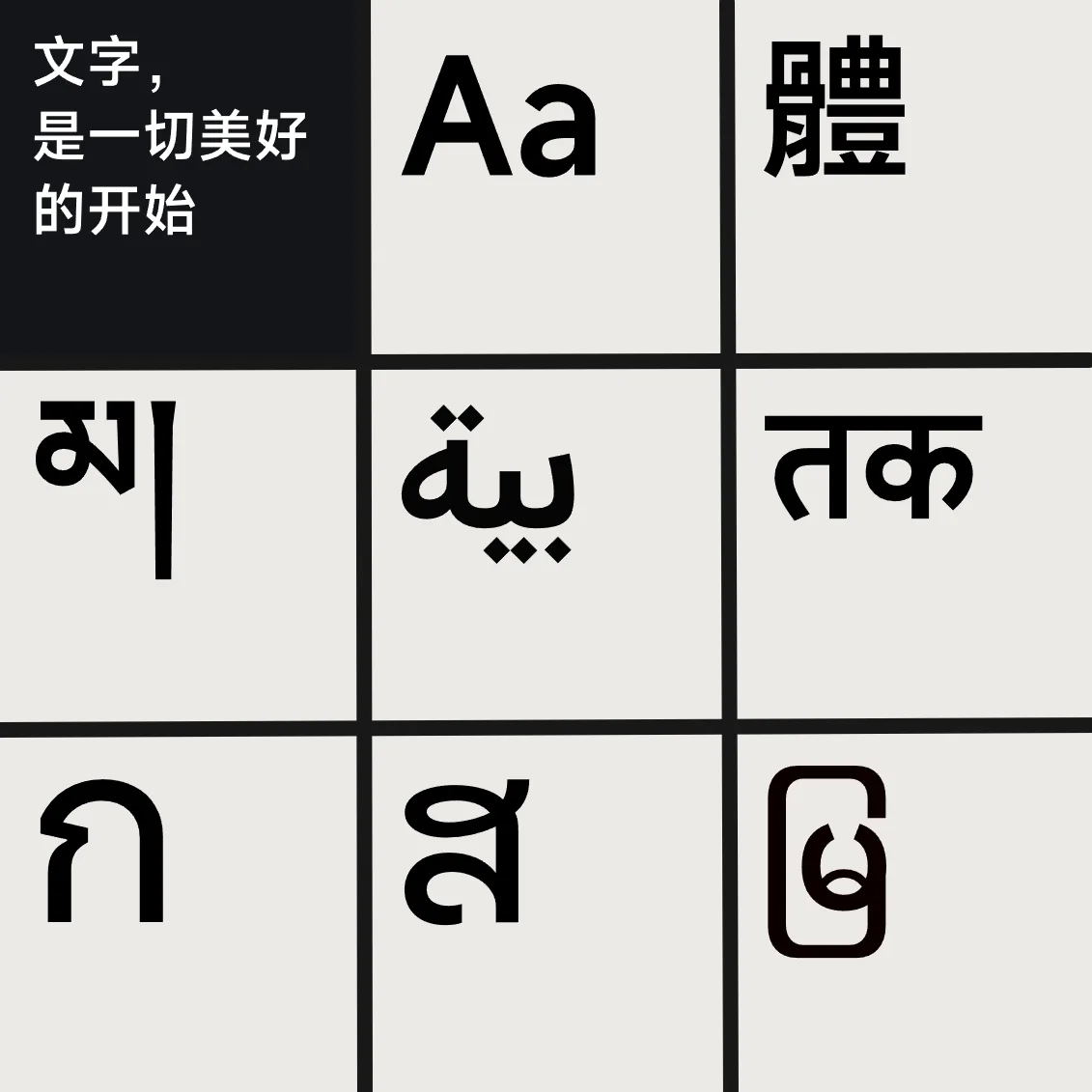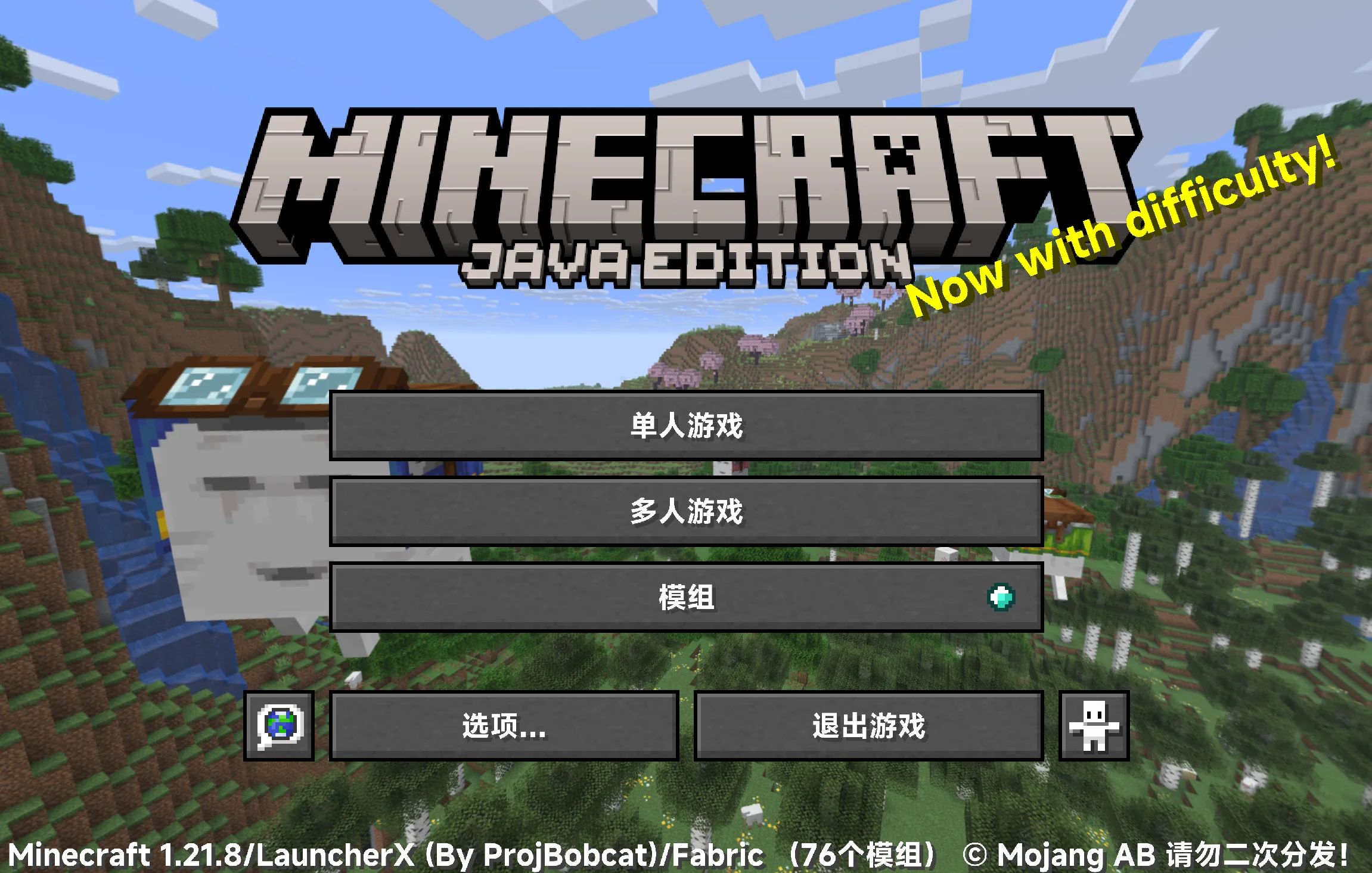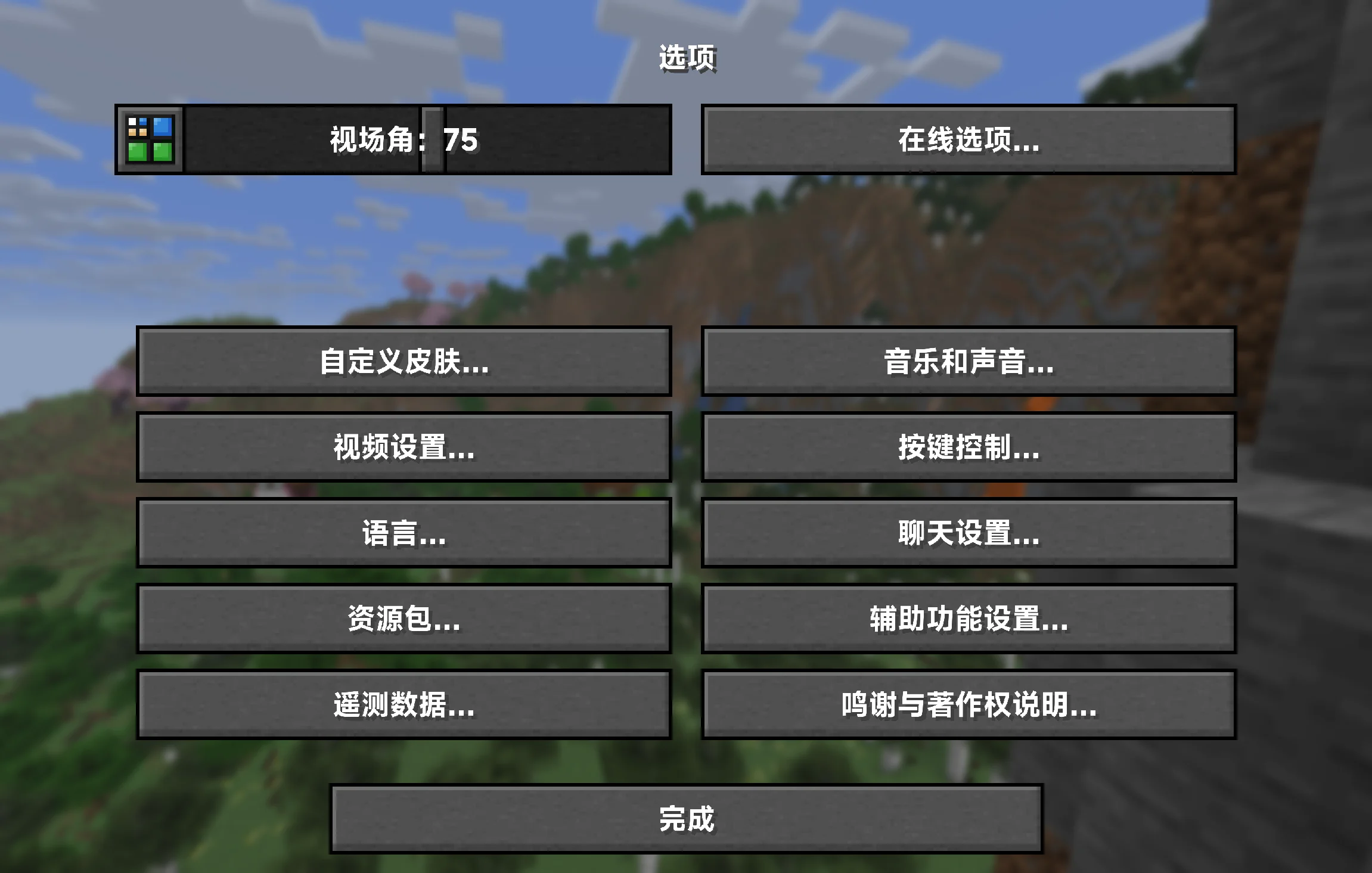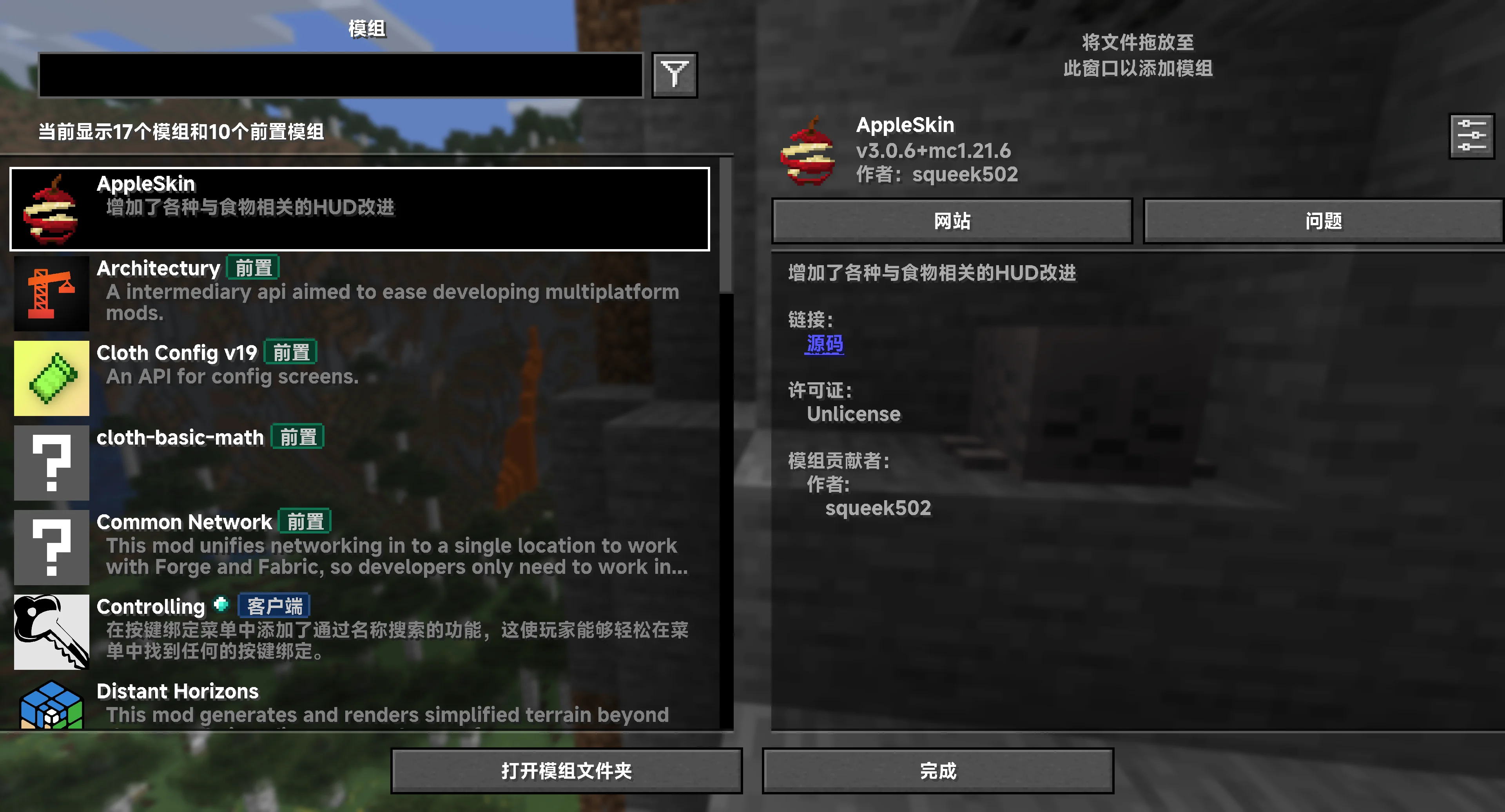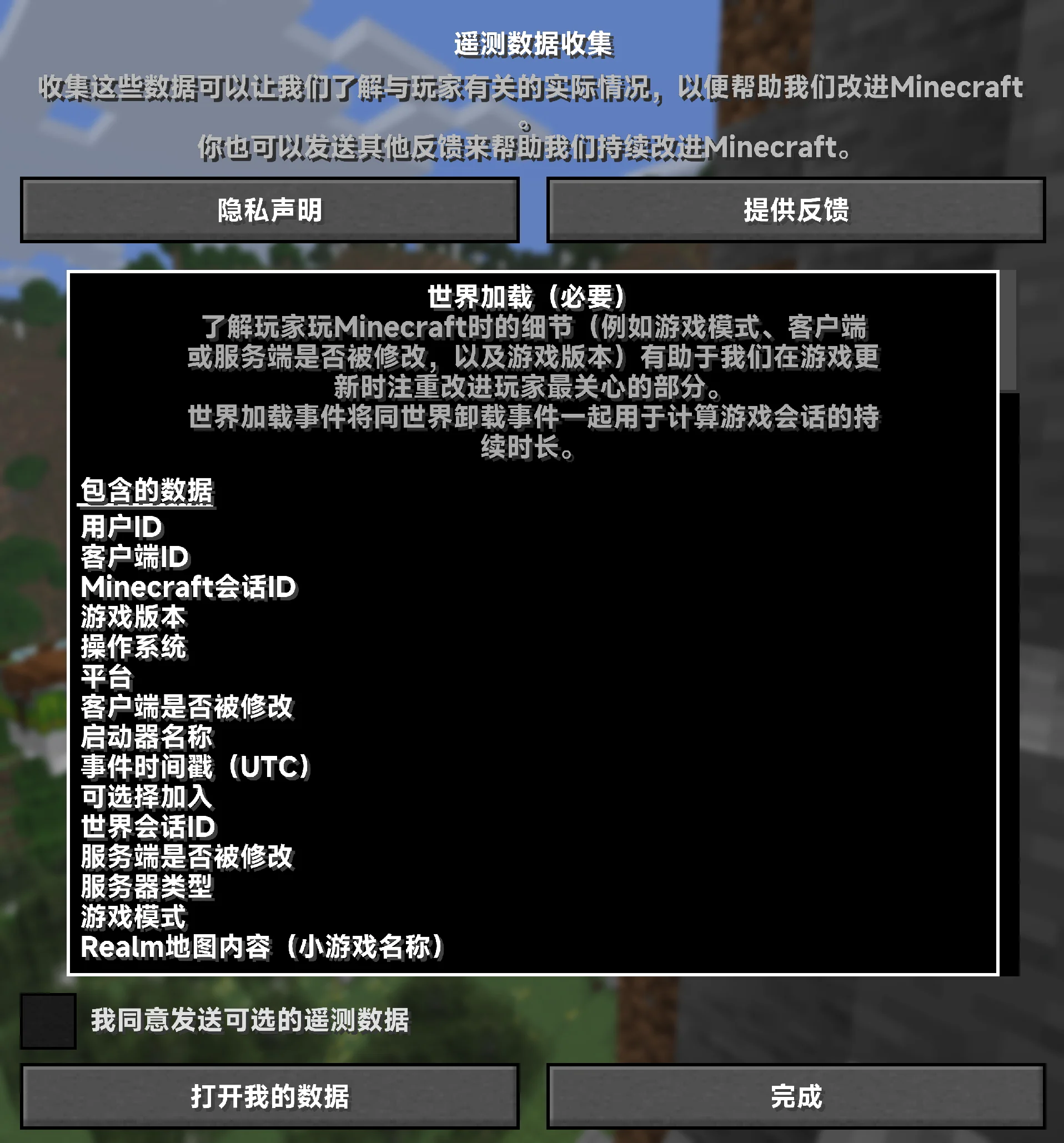
Ресурспак заменяет стандартный пиксельный шрифт на гладкий, улучшая читаемость текста в интерфейсе и чате. Не требует модов и совместим с большинством версий Minecraft.
Misans平滑字体包 — это ресурспак, который заменяет стандартный пиксельный шрифт Minecraft на гладкий и современный, обеспечивая чёткое и комфортное чтение текста в интерфейсе, чате и на табличках. Он не требует установки модов, таких как Caxton или ModernUI, и работает как чистый клиентский пакет, не влияя на сервер.